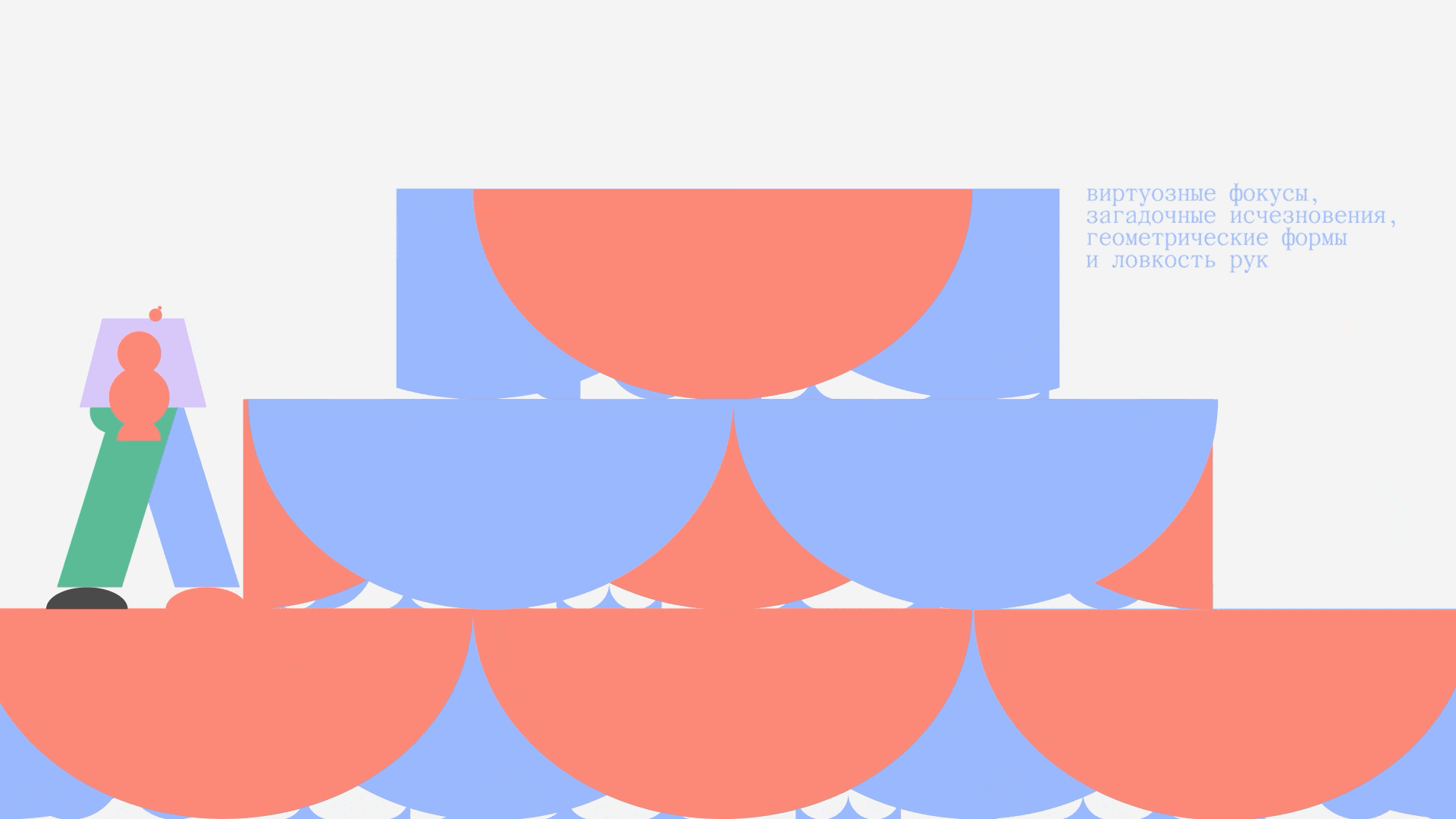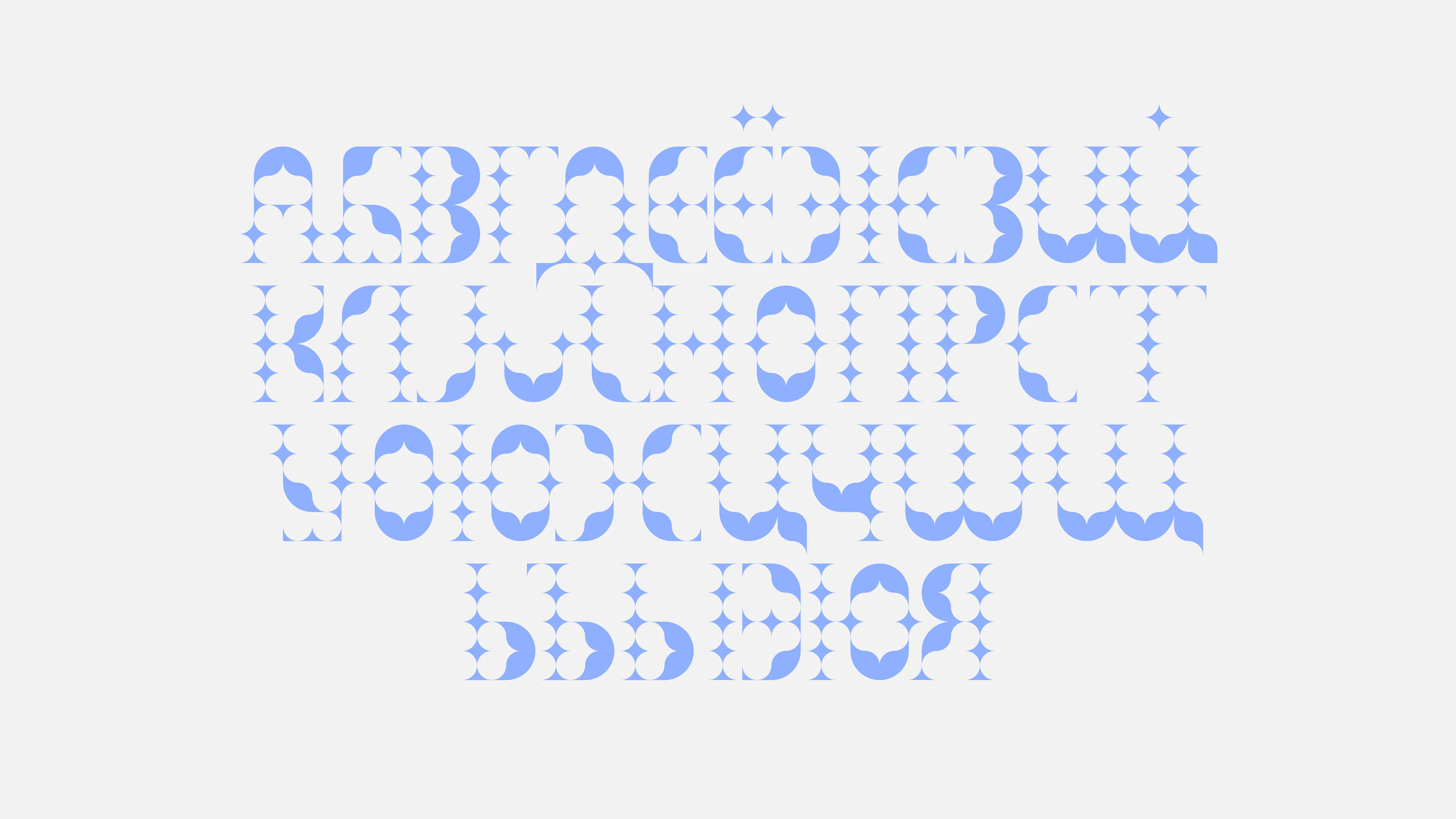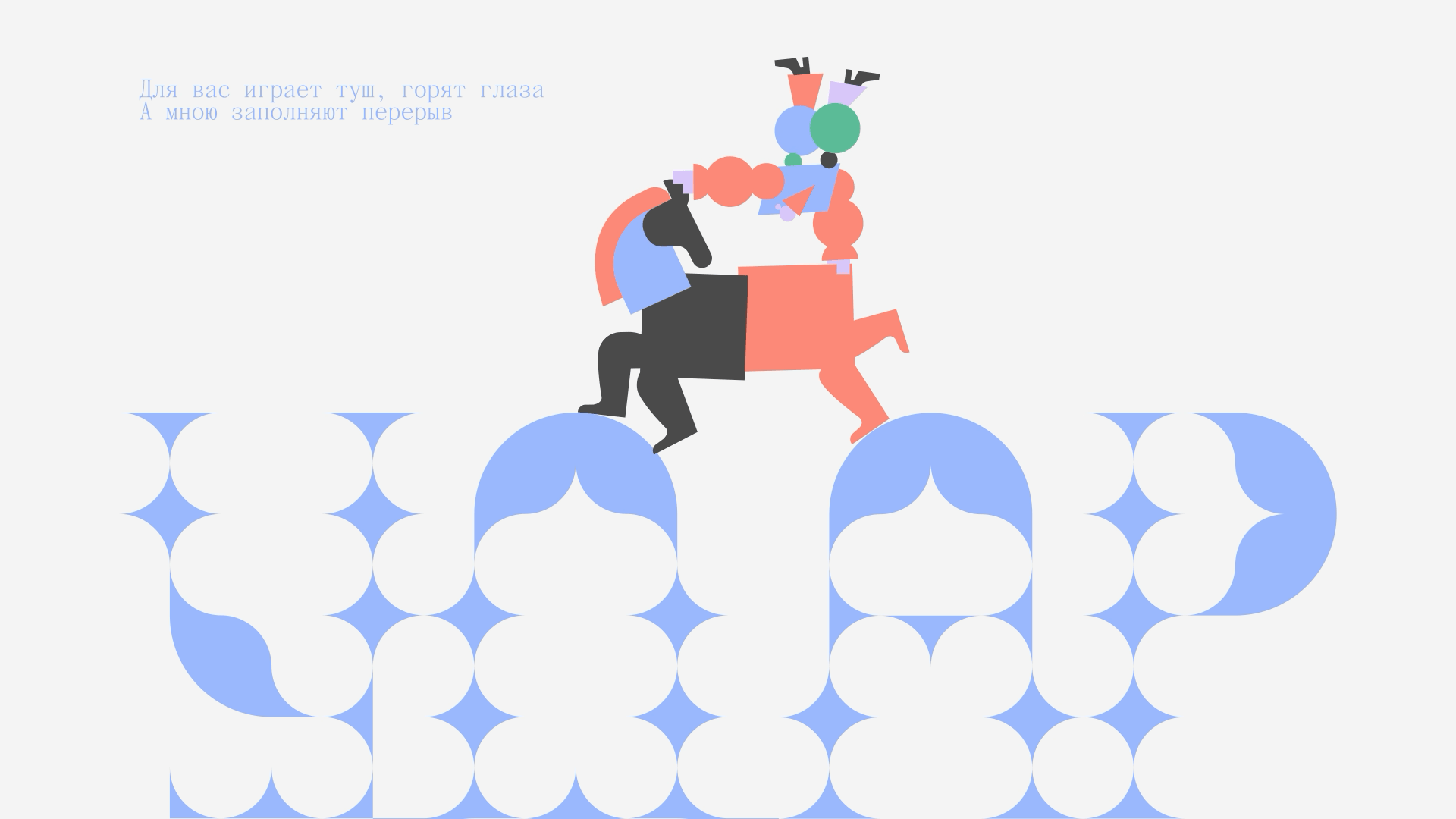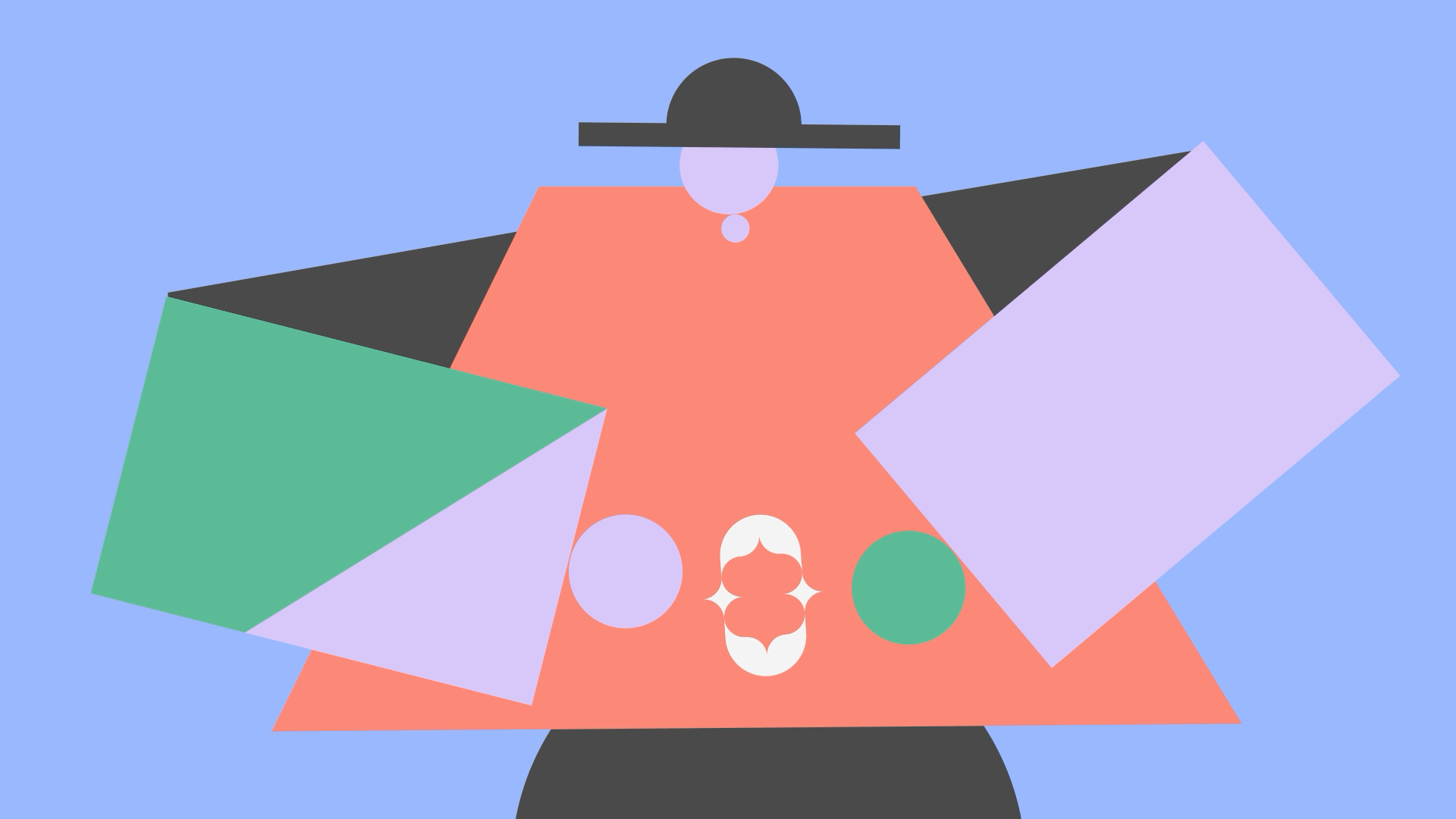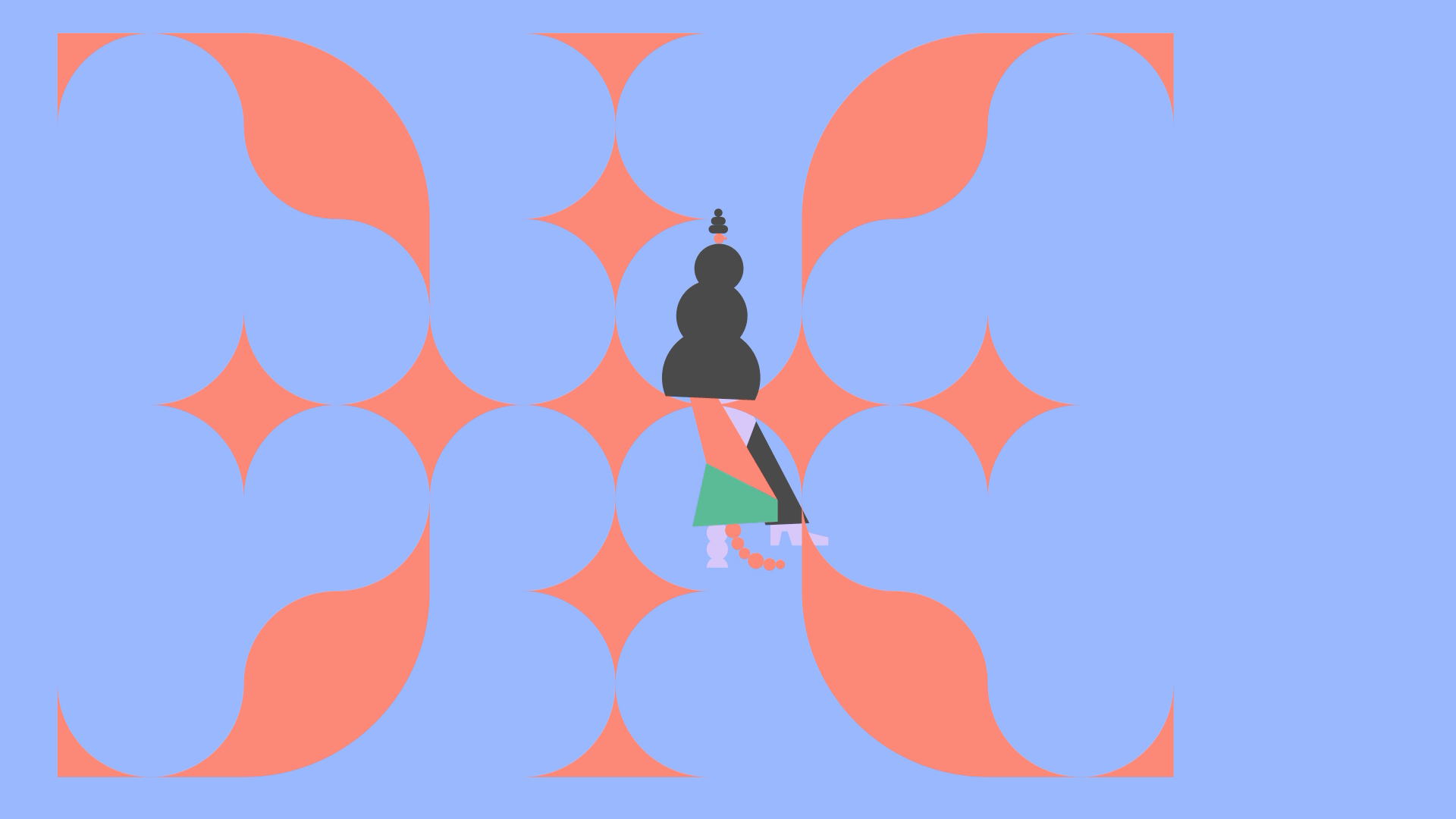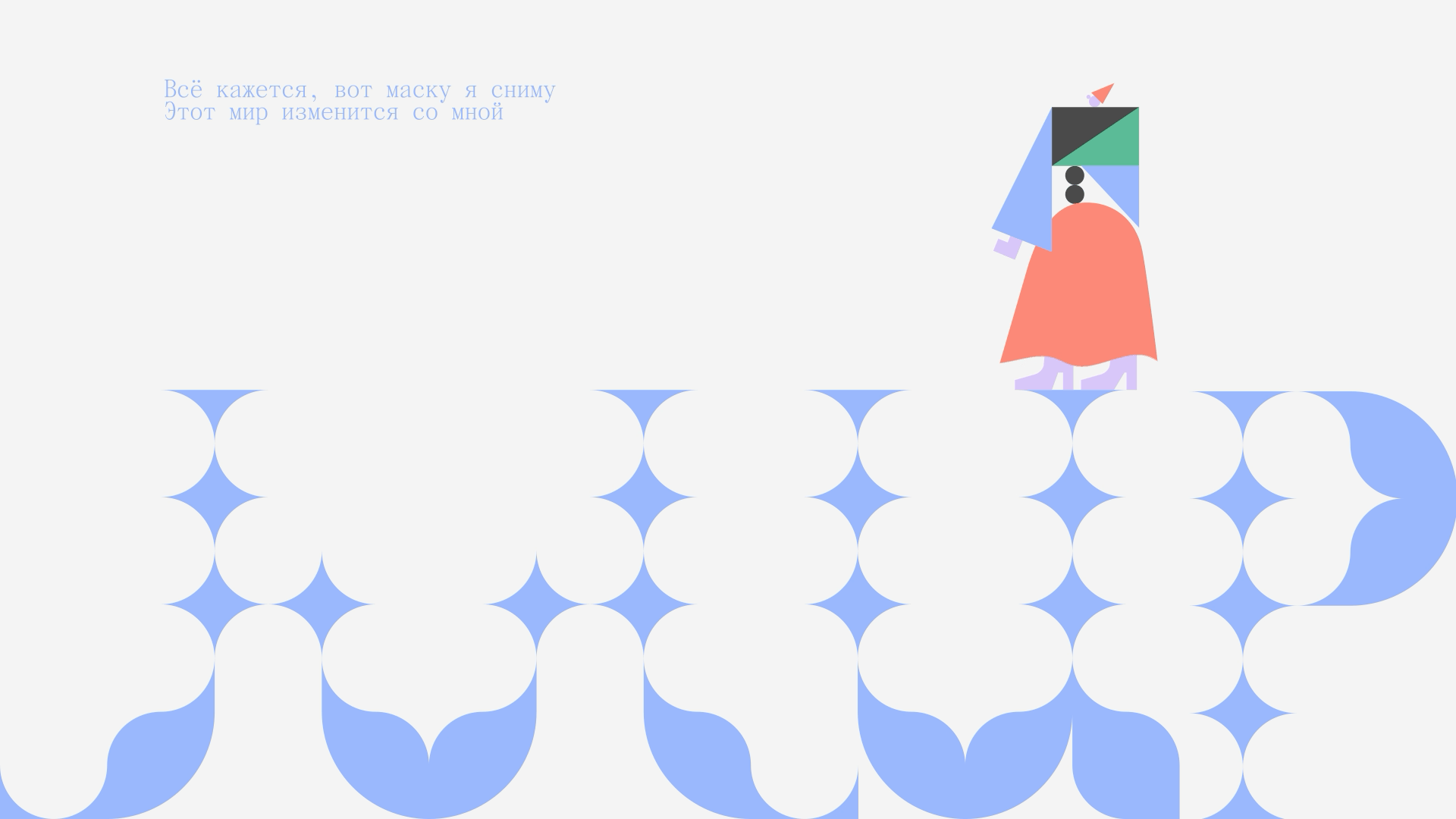
Brevitas font
Brevitas — это шрифт, где каждая буква словно создана из звездной пыли. Внутри этих сияющих
форм живут маленькие циркачи: они катаются по линиям, играют с формой и ритмом, расставляют
акценты и оживляют слова.
Brevitas — это спектакль, где буквы и циркачи вместе создают магию.